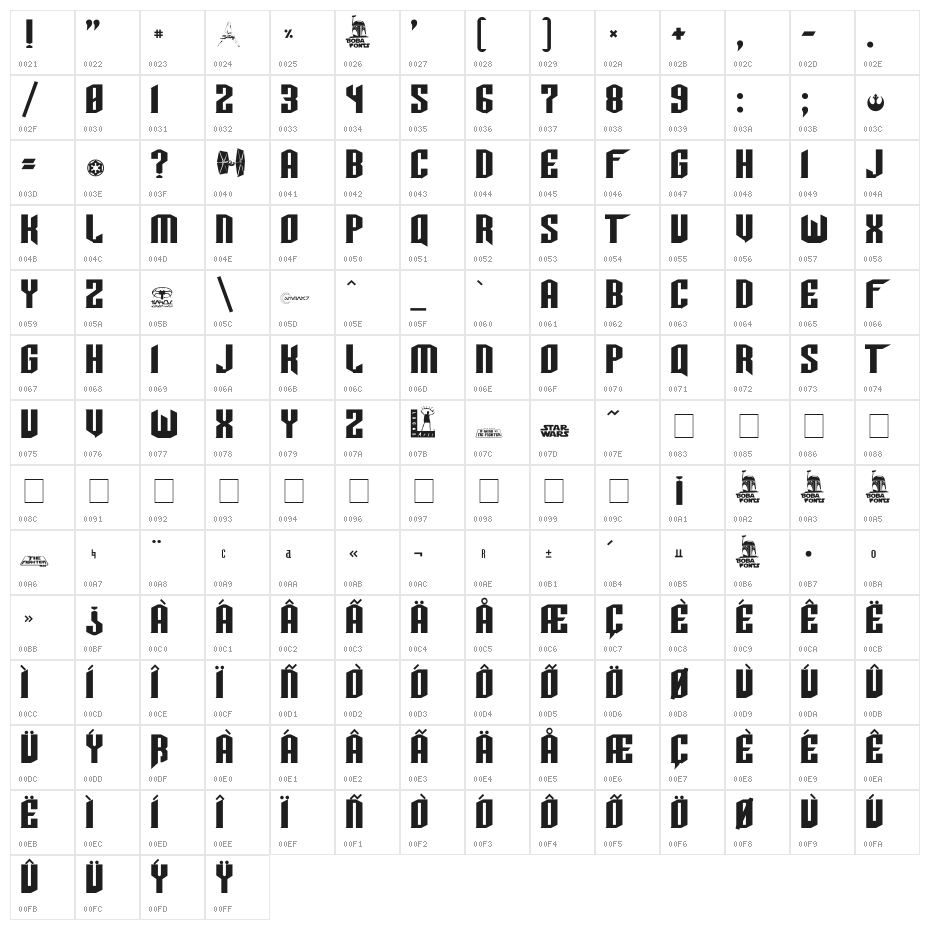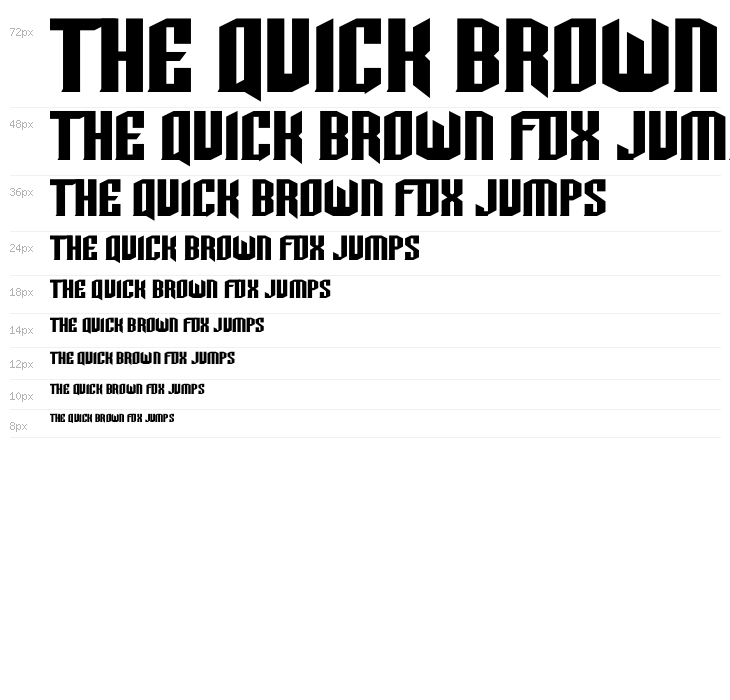
TIE-Wing Font
| Style général | Futuristic, Sci-Fi, Modern |
| Projets proposés | Ideal for video game titles, sci-fi movie posters, tech branding, and futuristic designs. |